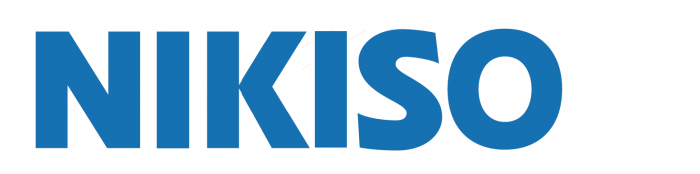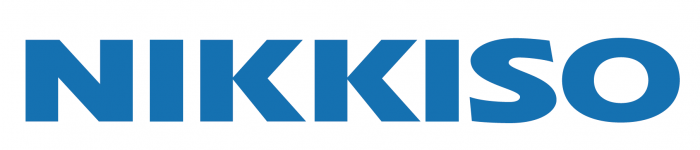
Schrift aus Logo gesucht
Irgendwie kommt sie mir verzerrt vor … Ein Versuch, sie zurückzuzerren, wobei ich rein nach Gefühl vorgegangen bin:
Das zurückgezerrte "R" kenn ich doch irgendwo her …
Das N und das K erinnern mich an Nokia. Auch dass das I nach links zu kippen scheint, ist bei Nokias Logo so.
Habe ich eigentlich einen Knick in der Pupille oder scheinen die Glyphen wirklich eilend zur Seite davonzustreben? (Sowohl in Bertels Beispielen als auch bei der Eras)
Das R in NIKKISO? ;-)
Eine verzerrte und in den Strichverläufen begradigte Eras Bold? Das S ist jedenfalls typisch Eras.
Das sind die Auswirkungen fehlenden Koffeins ;-) Natürlich meinte ich das S.